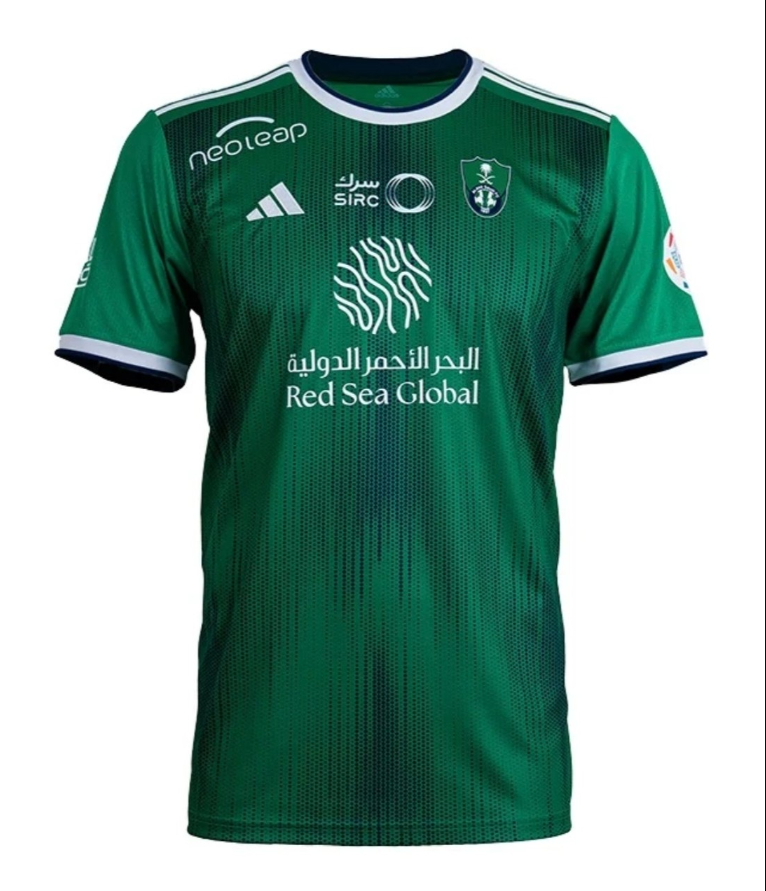
Fonte Al-Ahli SFC 2025/2026 (Adidas) – Download TTF & Vetor para Personalização
A Saudi Pro League continua sendo o centro das atenções no futebol mundial, e o Al-Ahli SFC, um dos gigantes de Jeddah, chega para a temporada 2025/2026 mantendo a elegância de sua parceria com a Adidas.
Se você trabalha com personalização de camisas ou design esportivo, ter a tipografia correta deste clube é indispensável. Afinal, é com essa fonte que grandes nomes como Roberto Firmino, Riyad Mahrez e Gabri Veiga estampam seus nomes nas costas do manto sagrado.
Estilo Visual e Aplicação
A tipografia desenvolvida pela Adidas para o Al-Ahli nesta temporada segue um padrão moderno e aerodinâmico. O design prioriza a legibilidade à longa distância — essencial para transmissões de TV — mas sem perder o estilo.
Os números possuem cortes geométricos precisos, característicos das fontes globais da marca alemã para seus clubes de elite (“Elite Teams”). A fonte transmite profissionalismo e velocidade, casando perfeitamente com o visual limpo e tradicional da camisa branca do clube. É a mesma tipografia vista na AFC Champions League Elite e nas competições domésticas sauditas.
Dica de Design: Para um acabamento 100% fiel ao original, utilize a cor verde oficial do clube (Green Pantone) para a numeração na camisa Home e preste atenção ao espaçamento (kerning), que costuma ser levemente mais aberto nas camisas da Adidas.